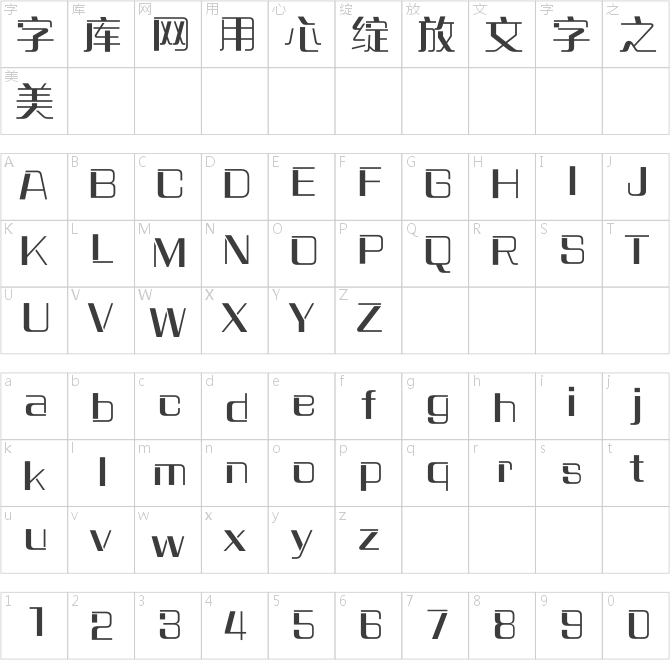
字體名稱: 方正晴朗體 簡
方正晴朗體 簡 DemiBold
方正晴朗體 簡 DemiBold介紹
方正晴朗體 簡 DemiBold字體字庫是一款讓人賞心悅目、百看不厭的中文字體,適合各類廣告和產(chǎn)品包裝設(shè)計應用,字體大小2.46MB,格式為ttf字體,上傳用戶是董志高,作者/版權(quán)方為方正字庫